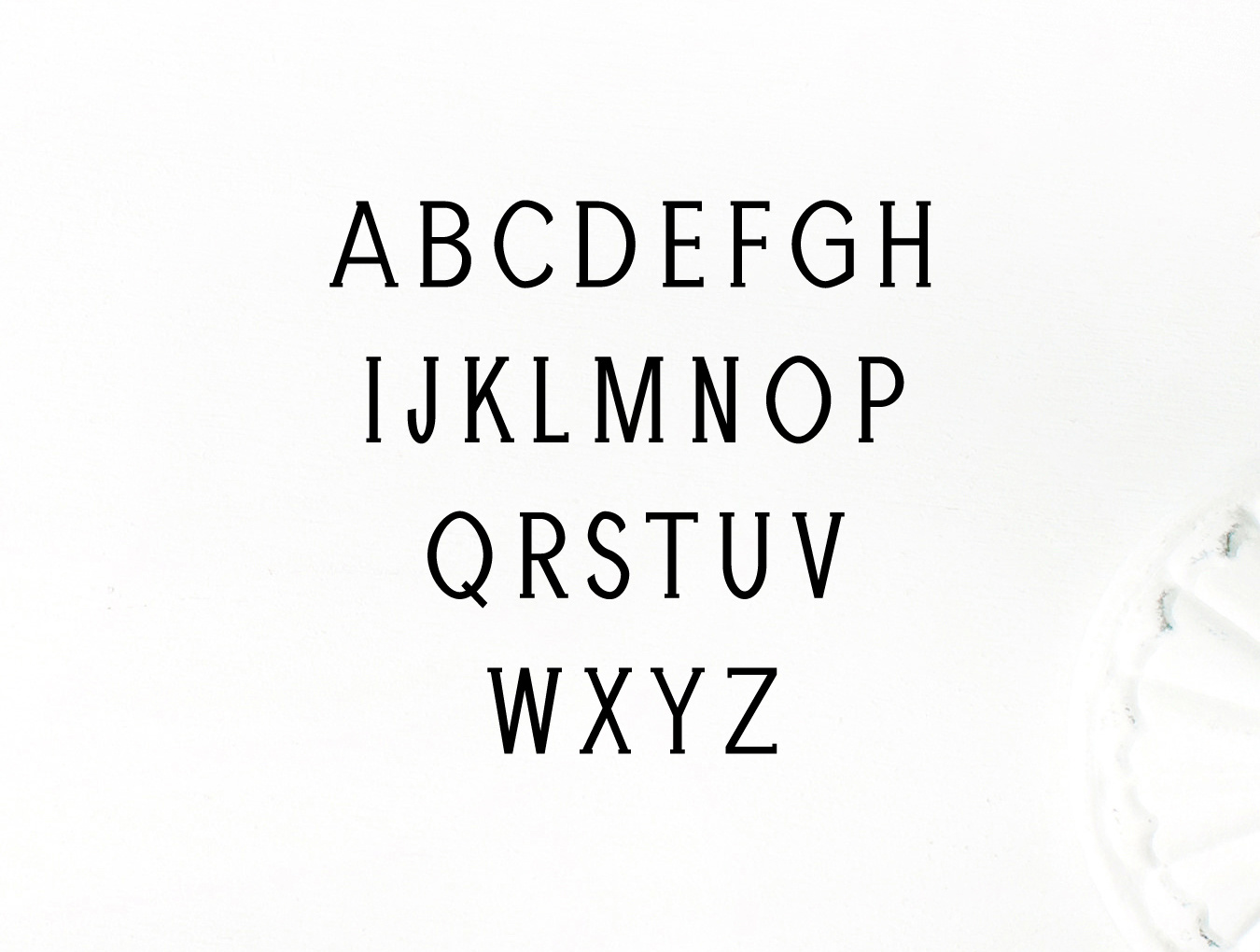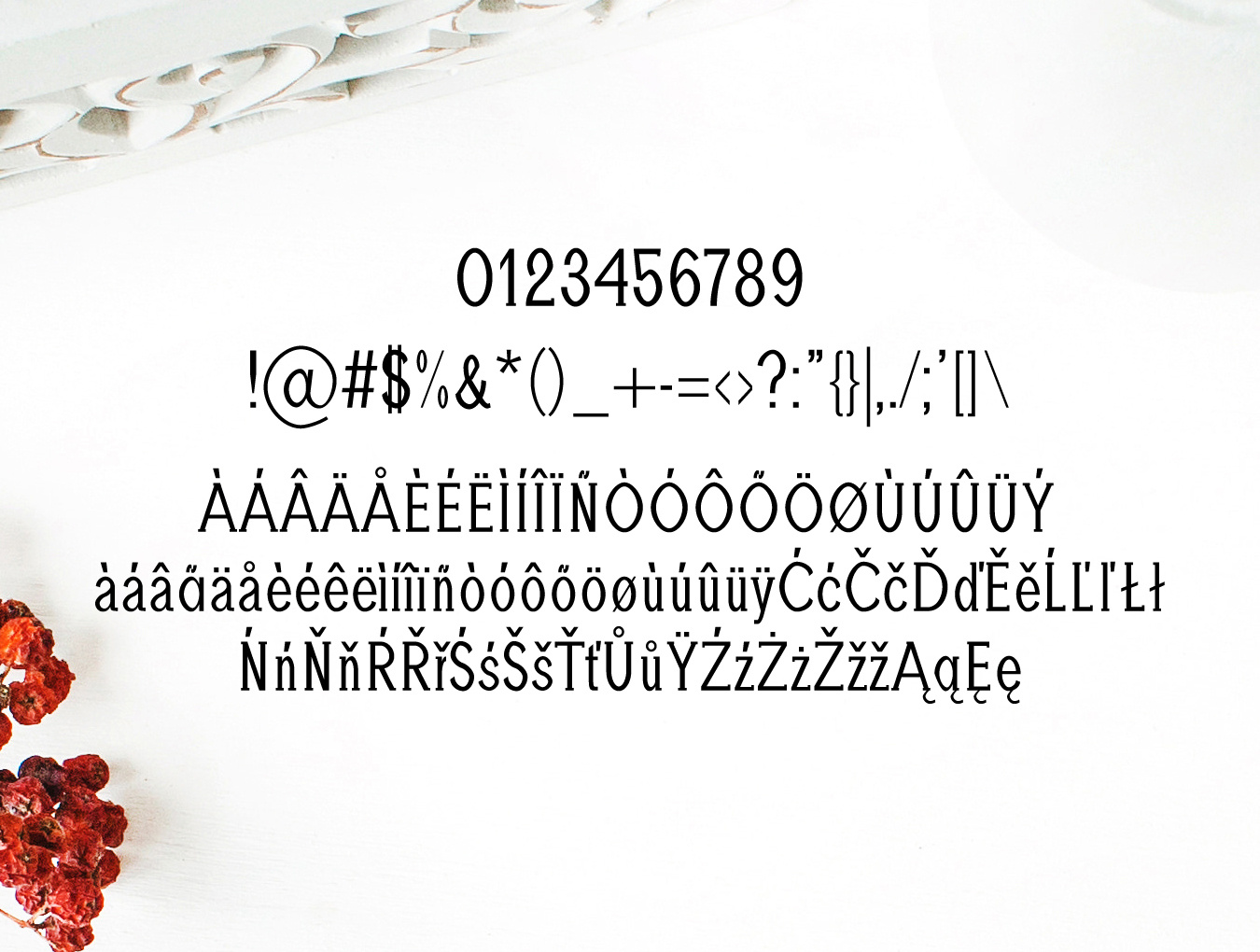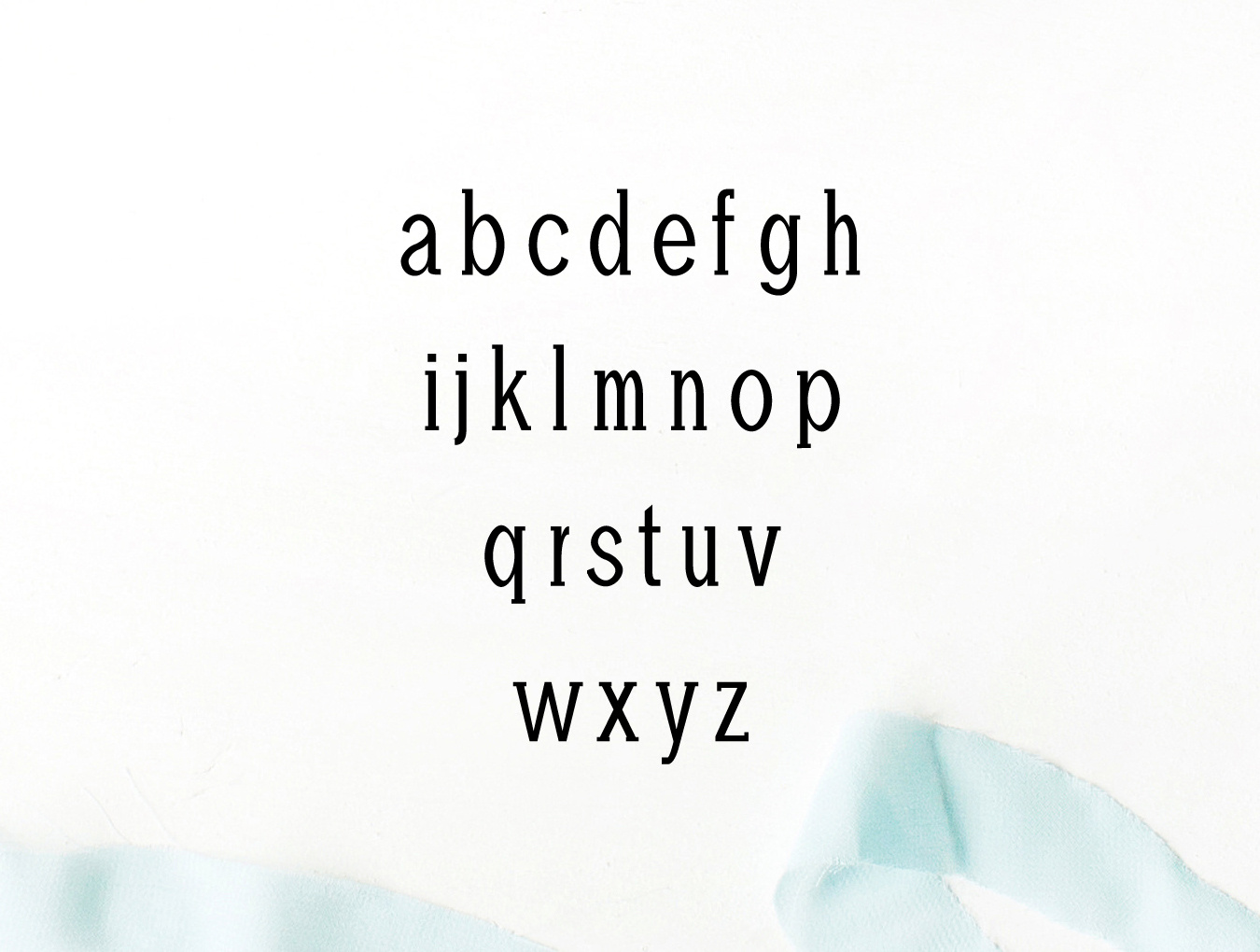
Adney Slab Serif 3字体家庭装,Adney Slab Serif字体
Adney Slab Serif 3 Font Family Pack, Adney Slab Serif Typeface
Adney Slab Serif Typeface是一套包含3个重量,适合制作创意展示。它是我们商店中可爱而独特的平板衬线字体,让您可以让每个单词看起来都非常时尚!它最适合现代/干净的设计,标识,标题,横幅和模板等。如果你想尝试一个优雅的外观,它看起来华丽的所有大写间距,或美丽的大写和小写字母为完全永恒的东西。